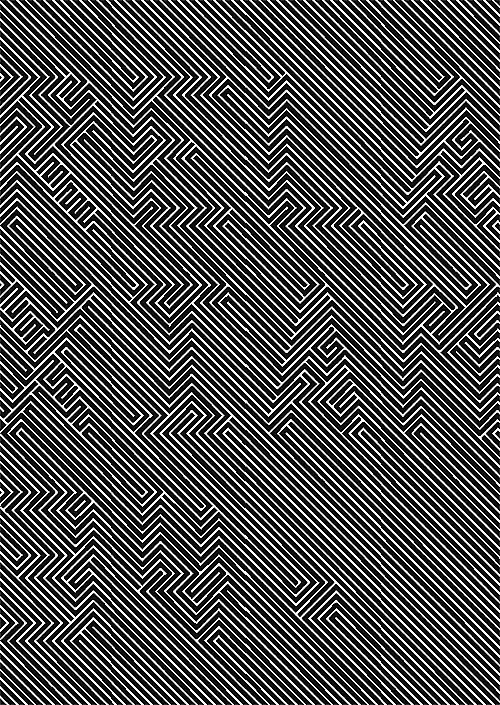
Schrift gesucht
Leider konnte ich den Titel nicht genauer spezifizieren, da ich mir nicht mal sicher bin, ob es sich dabei wirklich um eine Schrift handelt ... Ich kann mich allerdings dunkel daran erinnern, eine Diskussion oder einen Bericht schon einmal hier oder in der Page gelesen zu haben. Falls das Thema also schon x-mal durchgekaut wurde, pardon! Falls nicht, wäre ich um eine Antwort dankbar.
Es handelt sich um die "Schrift" auf angehängtem Beispiel. Gibt es irgendwas ähnliches in diese Richtung? Obwohl ich vermute, dass das Beispiel gezeichnet ist ... wüßte auch gar nicht, wie sich die Formen bei unterschiedlichen Zeichen so verbinden könnten.